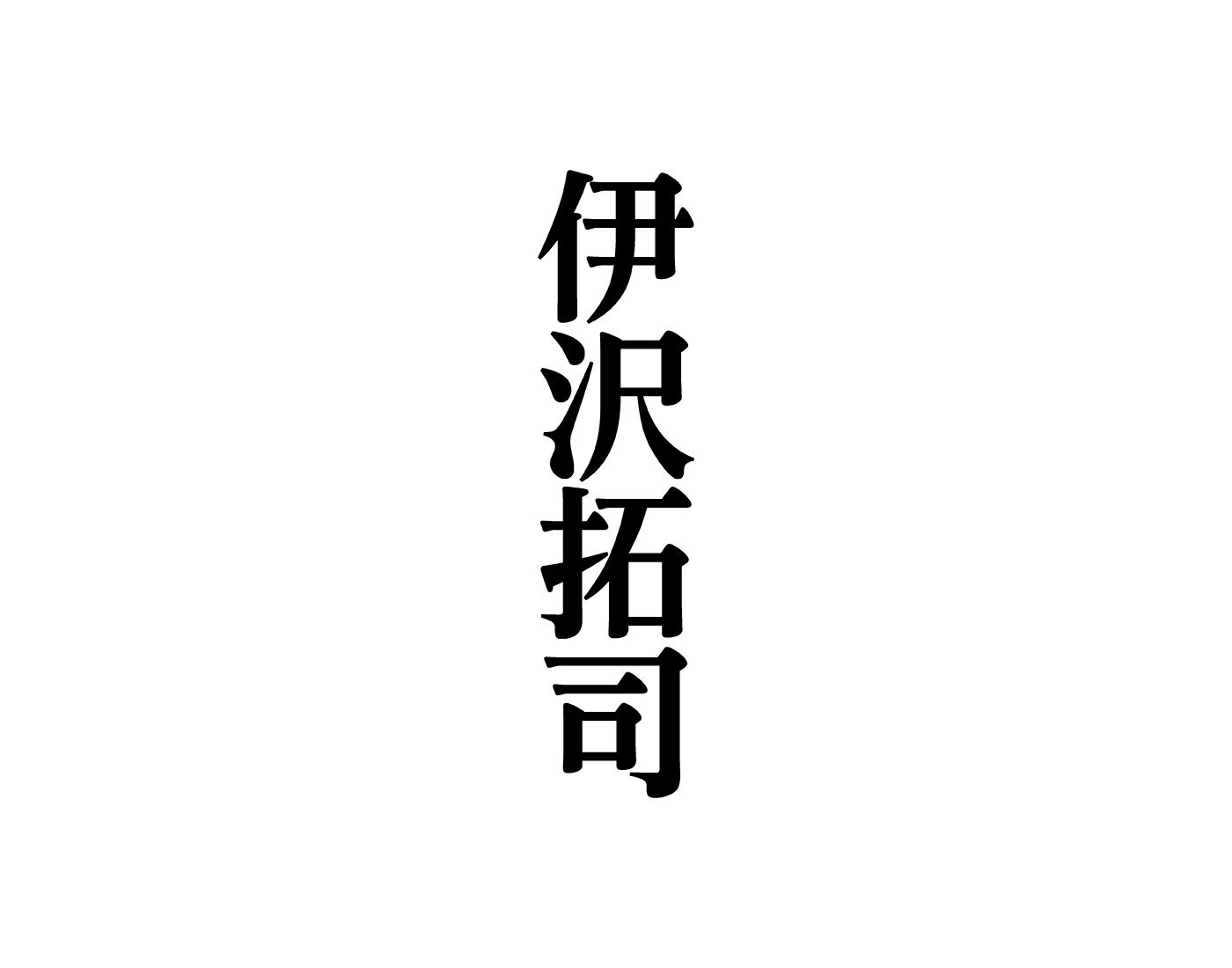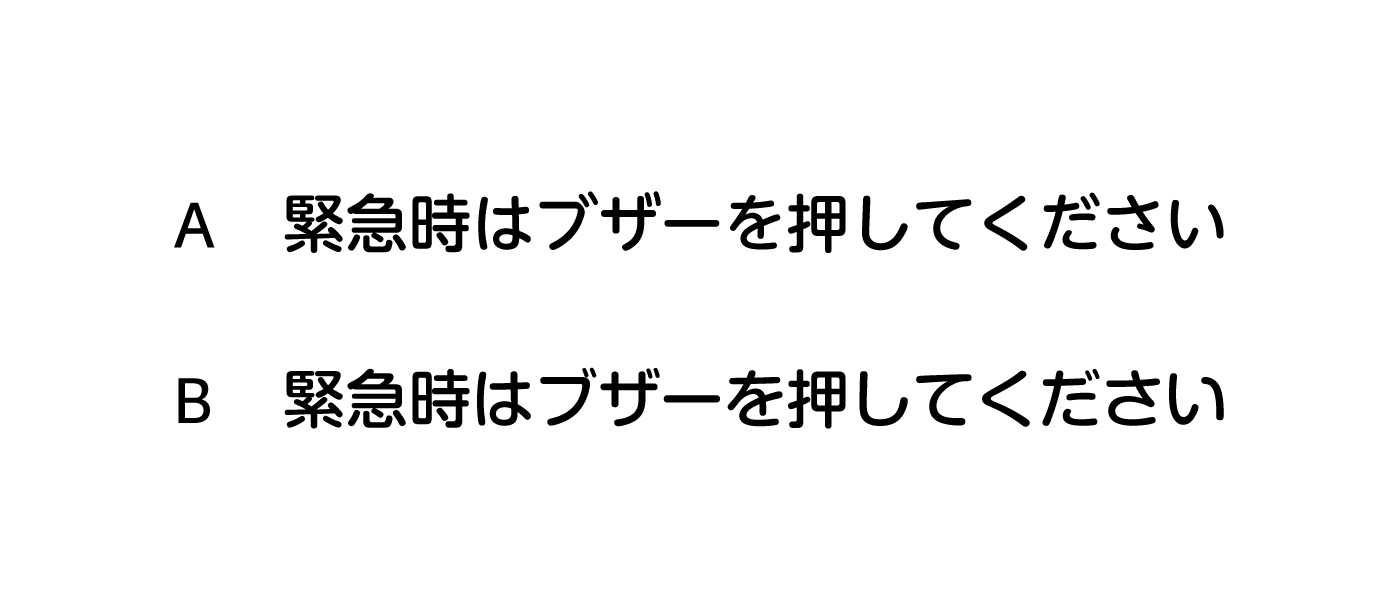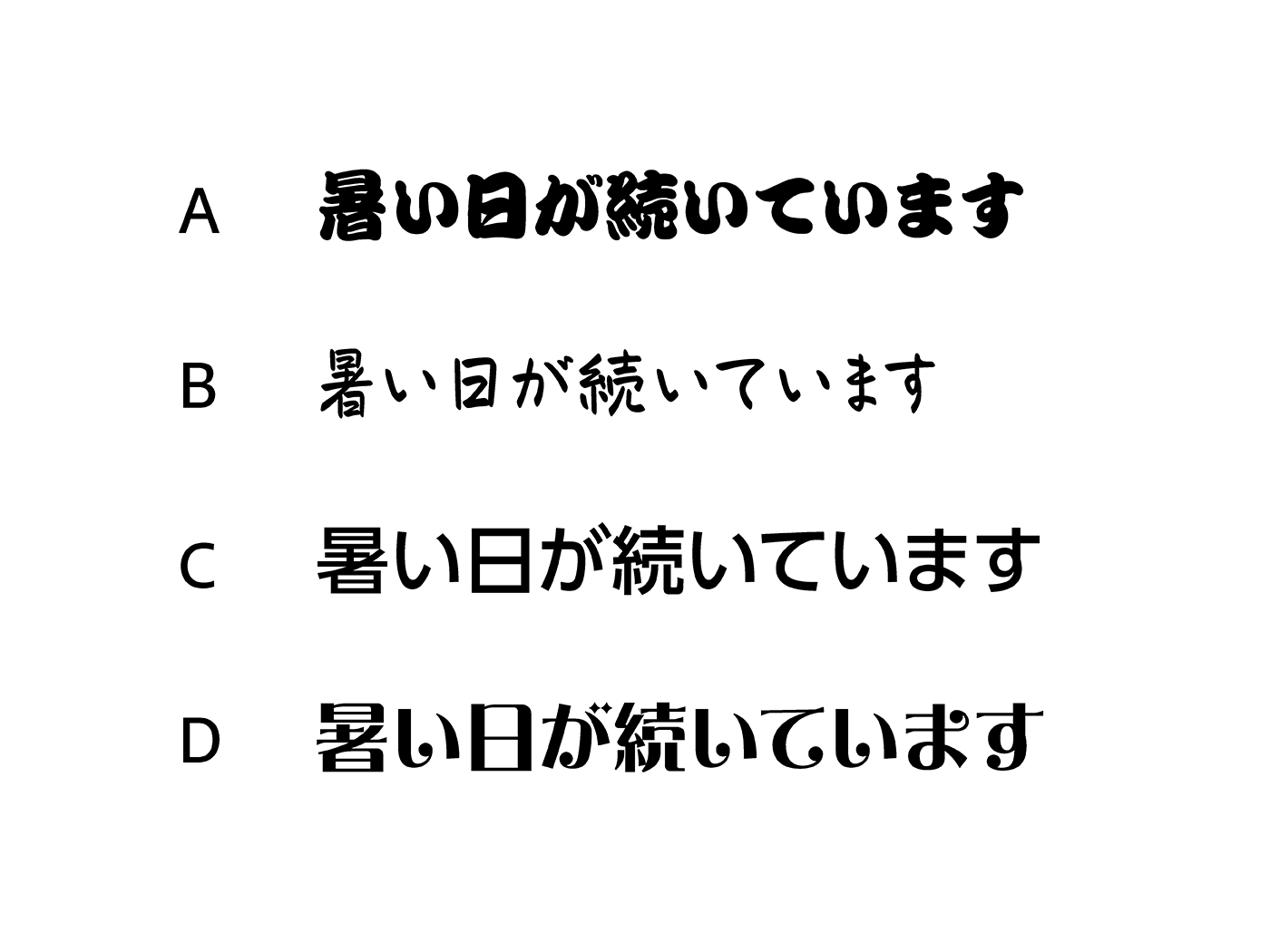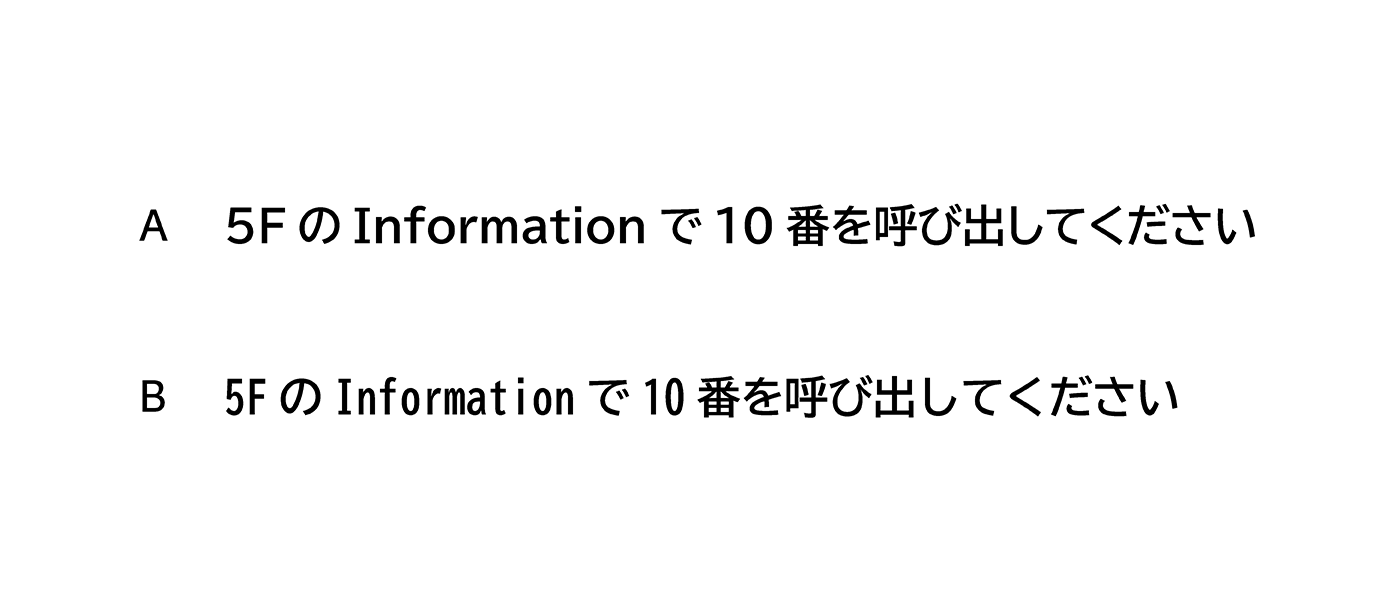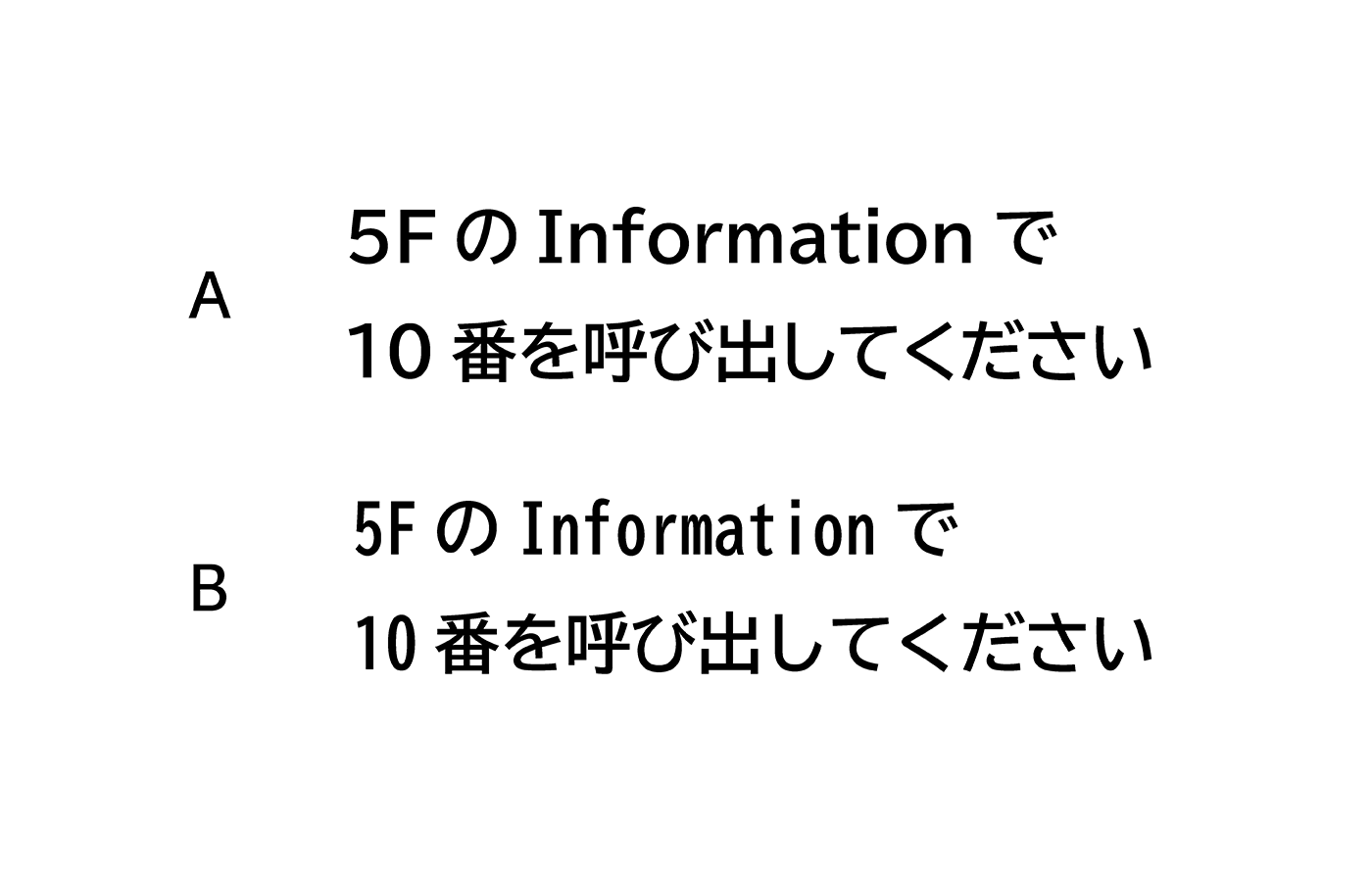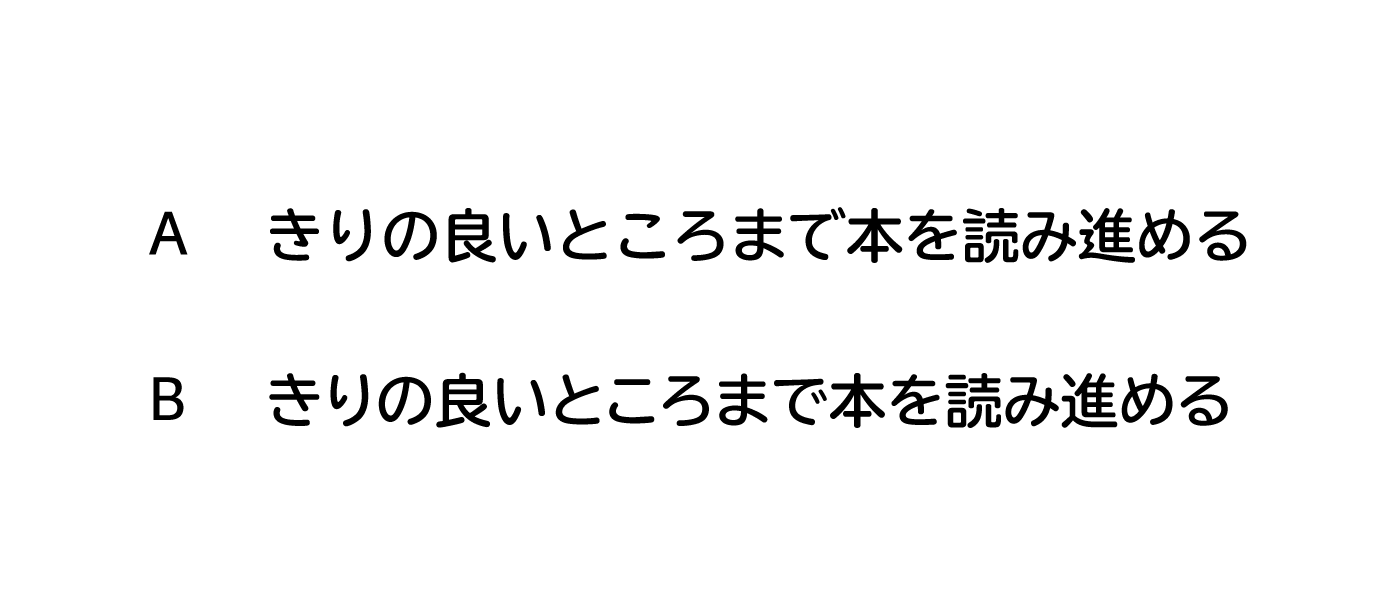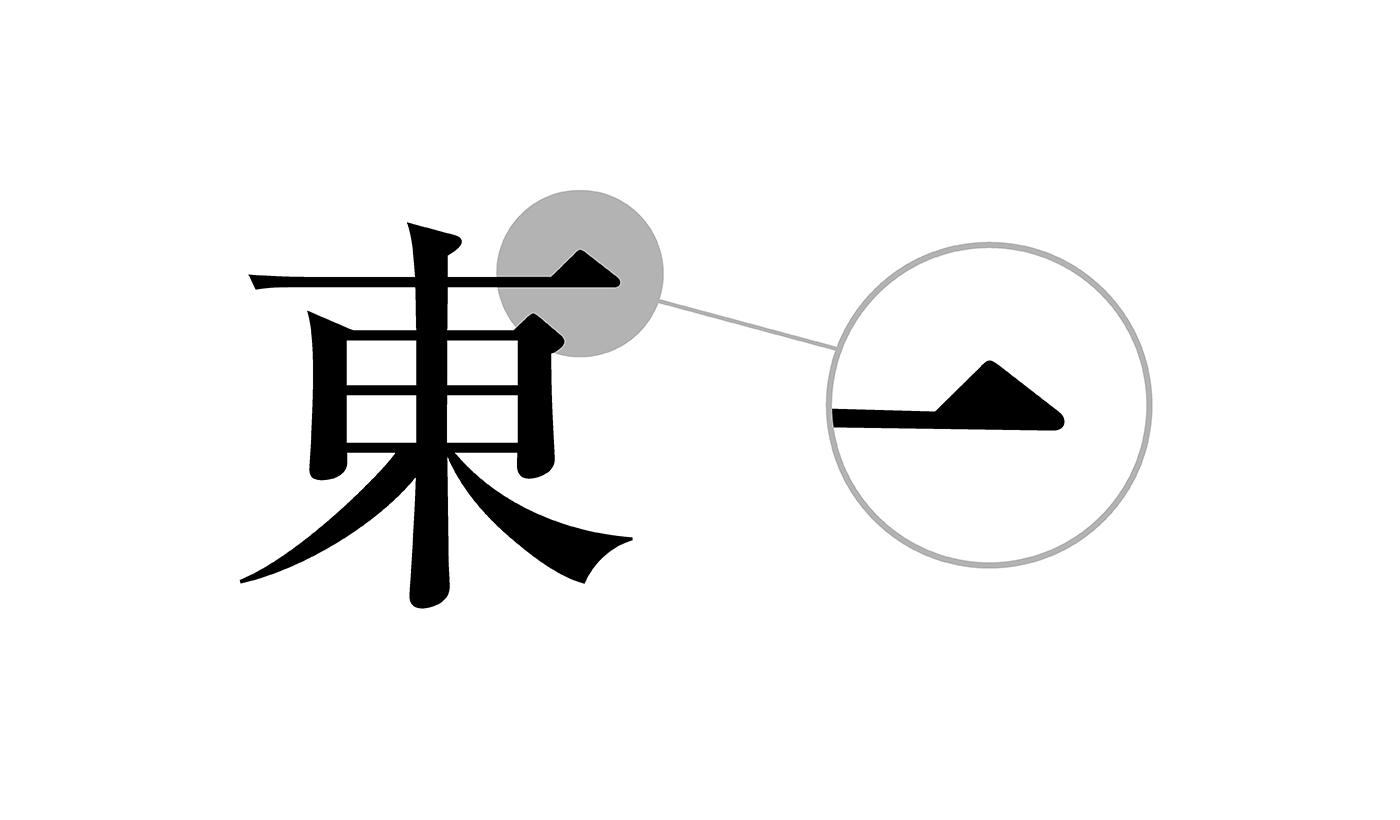
QuizKnockとモリサワのコラボクイズ!
知識集団・QuizKnock(クイズノック)とフォントのプロフェッショナル・モリサワがタッグを組んでフォントのクイズを作成!
問題は全部で10問。フォントマスターを目指して挑戦してみよう!
Q1
次のうち、一般的に明朝体がよく用いられるのはどれ?
Q2
次のうち、駅の案内標識などにも利用されている「UDフォント」と呼ばれるフォントはどっち?
Q3
次のうち、英語の「pen pal(文通友だち)」にちなんで名付けられた「ぺんぱる」というフォントを使って書かれている選択肢はどれ?
Q4
フォントには「BIZ UDゴシック」と「BIZ UDPゴシック」などのように、同じデザインにみえても名前に「P」がついて区別されているフォントがあります。
次のうち、「P」がつくフォントで入力した文章はどっち?
Q5
フォントを選ぶ際には、文字の大きさに合った太さのものを選ぶのが一般的です。小さな文字には細めのフォントを使う理由として、正しいものはどれ?
Q6
次のうち、教科書や参考書などで導入が進んでいるフォントはどっち?
Q7
モリサワの行書風デザイン書体である「澄月」が、書家の筆遣いを再現するために採用しているのはどんな仕組み?
Q8
明朝体の横画の右端に見られる、小さな三角形の装飾のことを何という?
Q9
こちらは新聞の本文用に作られたフォントです。このフォントを新聞紙面上と同じイメージにするには、どのように使うのが良い?
Q10
このフォントはどんな場所で使われているもの?